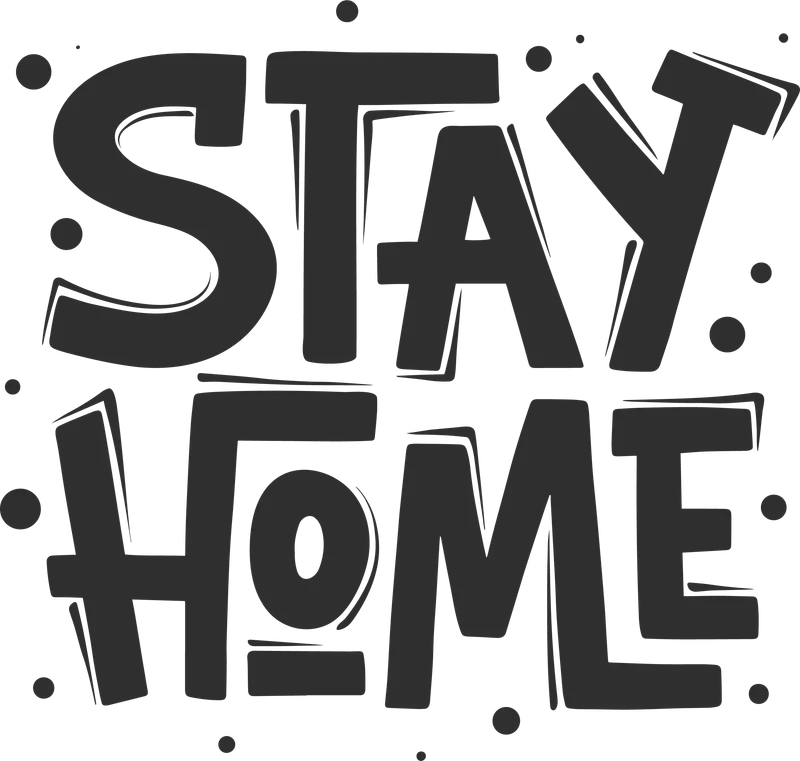
Thông điệp Stay Home ý nghĩa, font chữ độc đáo
Thông điệp Stay Home ý nghĩa, font chữ độc đáo — Thiết kế chữ 'STAY HOME' độc đáo, truyền tải thông điệp ý nghĩa về việc ở nhà. Phù hợp in áo thun, túi tote, sticker.
Trong hình có: chữ STAY HOME